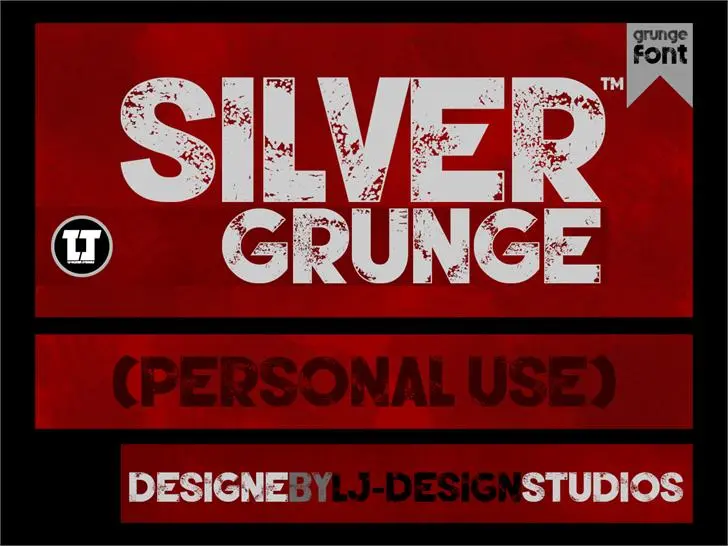
A Silver Forte Grunge é uma fonte sans-serif criada pela Hamilton em 2015. Inspirada nas fontes familiares mais tradicionais, ela incorpora elementos g rungeiros e personalizados para oferecer um toque único e inovador ao design. Com sua riqueza de detalhes e textura peculiar, a fonte Silver Forte Grunge traz uma sensação casual e descomplicada que se destaca em qualquer projeto. Através dela, designers podem encontrar o equilíbrio perfeito entre modernidade e personalização. Como parte da família Home variante, essa fonte oferece mais liberdade de criatividade para projetos pessoais e comerciais, sem se sacrificar pela simplicidade. Para uso pessoal com fins comerciais ou qualquer outra consulta sobre direitos autorais, lembre-se que você precisa entrar em contato através do endereço . Aproveite a gama única da Silver Forte Grunge para dar um toque único ao seu próximo projeto visual.